ATypI 2019 TOKYOでの講演「機械学習と書体開発」
「ATypI 2019 TOKYO」のレポート第2弾です。タイププロジェクトのインターン・日暮拓人によるプレゼンテーション「機械学習と書体開発」のダイジェストをお届けします。
「僕は今、芝浦工業大学の大学院でコンピューティングデザインの勉強をしています。学部時代は書体の特徴を維持した文字の自動デザインについての研究をしていました。今日はその研究をもとにお話しします」
「今回作成したシステムでは、既存のフォントからたくさんの文字をディープラーニングで学習させます。具体的には何百種類ものフォントから2文字のペアを作り、そのペアの特徴をディープラーニングによって見つけ出してもらいます。実際に自動デザインを行う際には、1文字を入力とすることで、学習した結果から、ペアになるであろうもう1文字を作り出すことができます。ここで注意したいのは、決して学習したものの中から近いものが出力されるのではなく、コンピュータがゼロからデザインした新しい文字が出てくるということです」
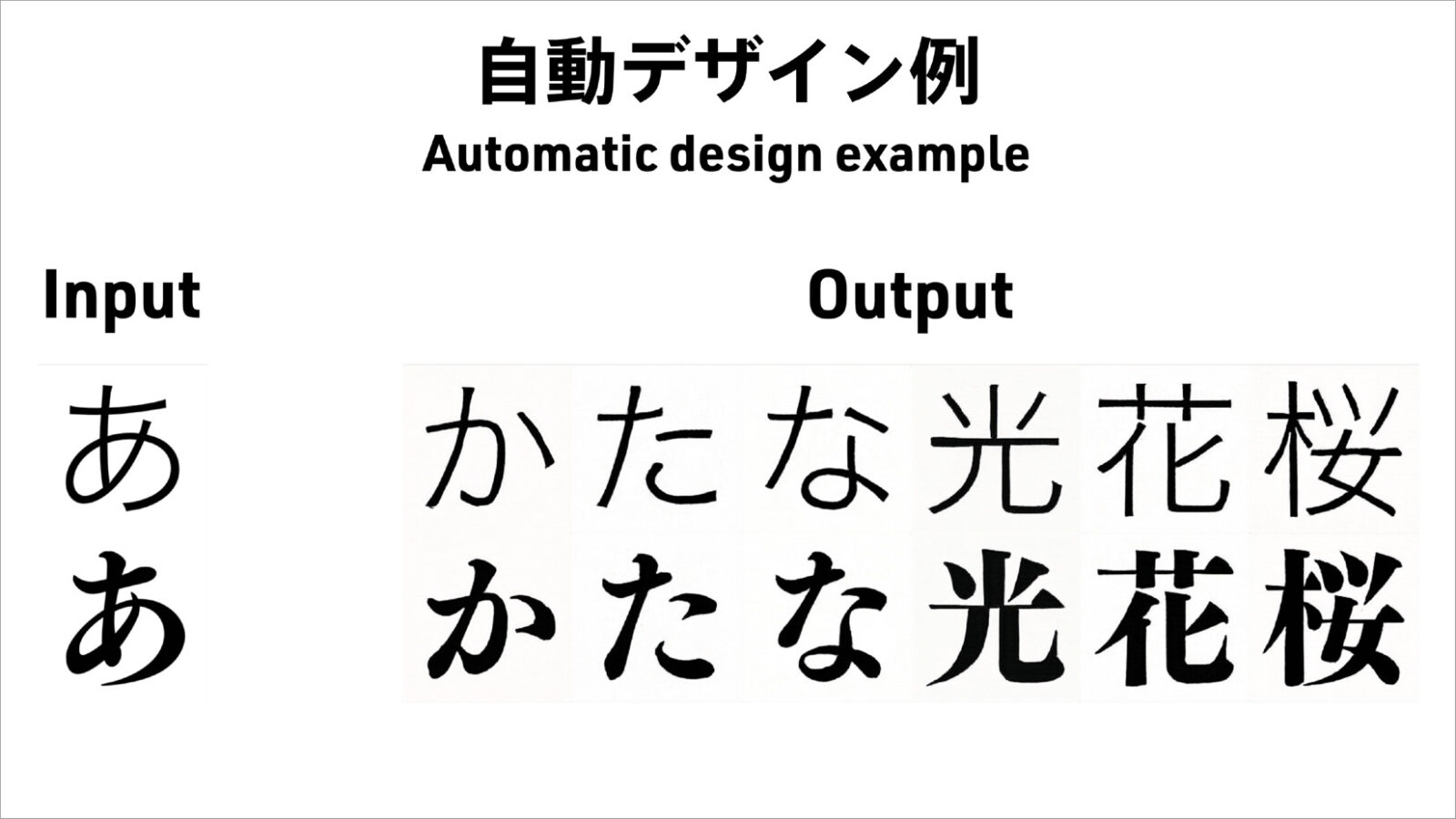
「次に品質保証に使える機械学習技術の紹介です。このFont Finderというのは僕の開発したサービスなのですが、たった1文字の画像から候補となる書体を提示してくれます。このような技術は、クオリティチェックに使えると考えられます。たとえば、メインデザイナーが作成した基本文字に対して、他のデザイナーの作成した文字がマッチするかといった場面や、デザイン案が複数ある文字で、最もその書体らしいデザインを判断することができます」
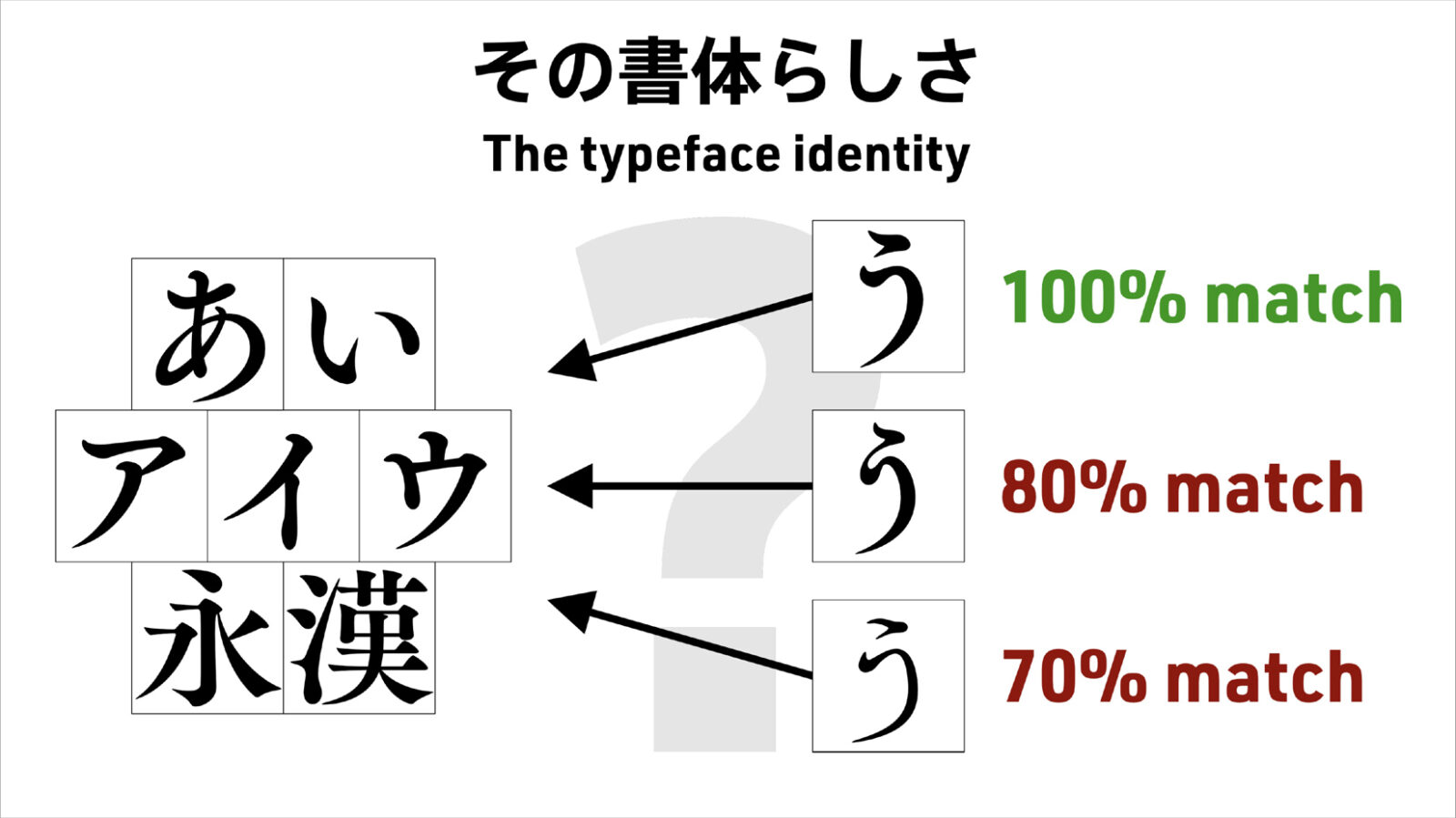
「最後に、今まで紹介してきた技術が実際の仕事などで使えるかどうか、僕の考えをお話ししたいと思います。現状として、仮名では人がデザインしたものと見分けのつかない精度でデザインができています。そして、画像を入力とすることで、その書体を数値化や書体判定を行うことができています。部分的には、すでに実用レベルで技術が発展しているのですが、課題もあります。まず第一に、まだ十分な精度があるとは言えません。また、これは書体開発に限らず多くの分野で言われていることですが、機械学習によって作られたデータの権利の問題があります。さらに、ディープラーニングでは内部がブラックボックス化されてしまうことが多いので、なぜそのようなデザインになったかコンピュータは説明してくれません」
「しかし、これらの問題が解決されていけば、自動デザインによる、大幅な作業の効率化が行えます。たとえば、先ほど紹介した自動デザインの技術では1文字デザインするのに1秒もかかりません。また、人の目だけではなく、機械的にデザインの品質確認を行えるため、より安定したデザインを提供することができるようになります。問題が解決されるのは遠い未来の話ではなく、今後数年の間には、本当に使える技術として登場すると考えられます。僕は現在、日本のフォントメーカーと共同開発を行なっており、大学でもこの研究を進めているため、また新しいことを発表できればと思います」